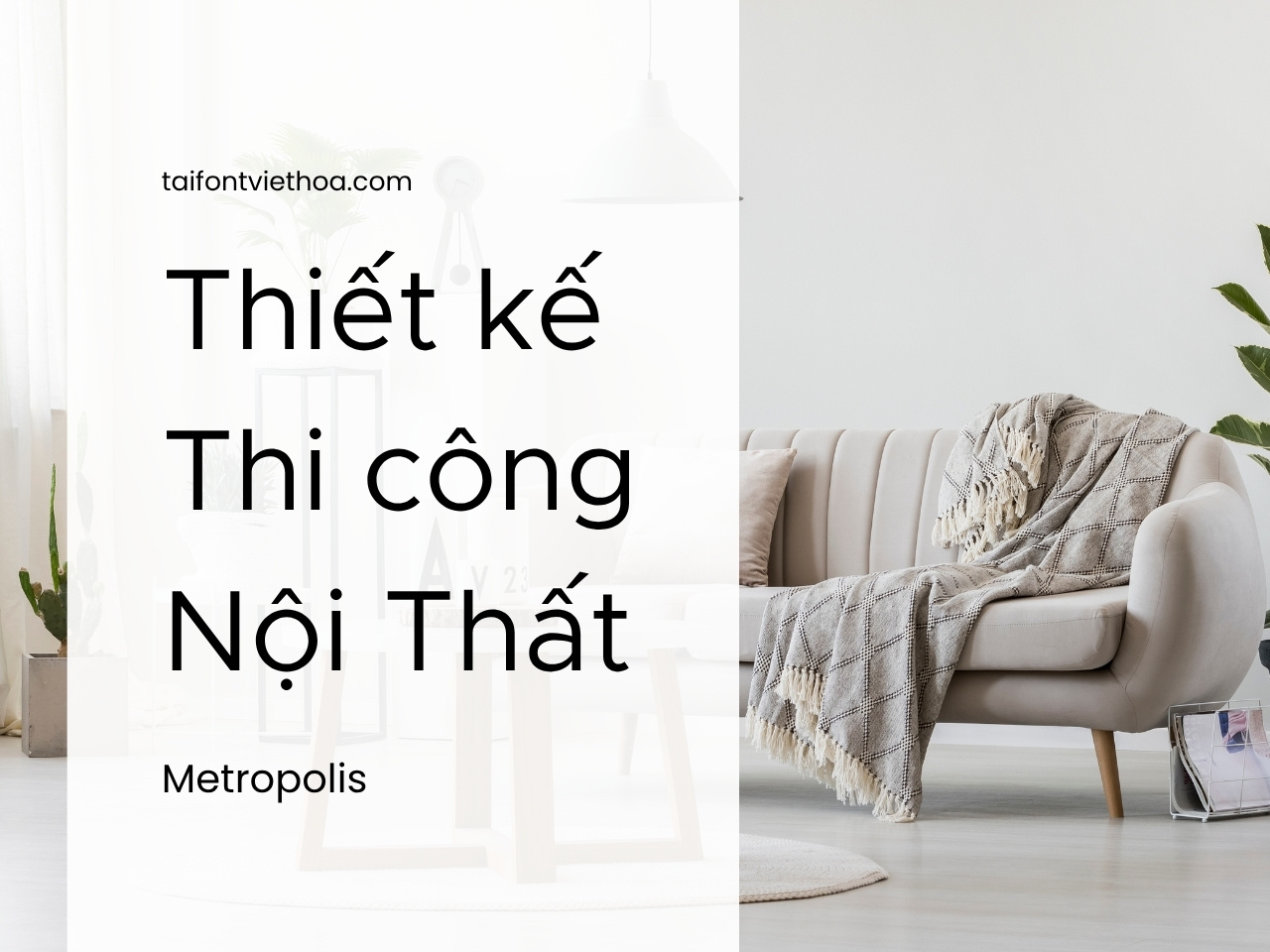
Font việt hóa Metropolis+
Tác giả Font: Chris Simpson
Giới thiệu về font Metropolis+
Metropolis là một font chữ sans-serif hiện đại theo phong cách geometric, được thiết kế bởi Chris Simpson vào năm 2020 và phát hành dưới giấy phép mã nguồn mở. Font được tạo ra như một lựa chọn thay thế cho các kiểu chữ nổi tiếng như Gotham hoặc Avenir. Phiên bản Việt hóa có tên Metropolis+ được thực hiện bởi Catterio, mang đến trải nghiệm đầy đủ cho người dùng Việt với hệ thống dấu tiếng Việt chuẩn và đẹp. Font còn hỗ trợ hơn 50 ngôn ngữ khác thông qua bảng mã Latin mở rộng, giúp nó trở thành công cụ lý tưởng cho các dự án đa ngôn ngữ. Font này được taifontviethoa.com sưu tầm, chọn lọc và thử nghiệm thực tế nhằm đáp ứng nhu cầu thiết kế đa dạng của cộng đồng sáng tạo tại Việt Nam.
Đặc điểm thiết kế và ứng dụng của Metropolis+
Metropolis+ sở hữu cấu trúc hình học rõ ràng, hiện đại, các đường nét tinh giản với độ dày đều và tương phản thấp. Font có 18 style từ Thin đến Black, bao gồm cả Italic, mang lại khả năng ứng dụng linh hoạt cho nhiều mục đích. Các ligatures và kerning được tinh chỉnh kỹ lưỡng giúp font hiển thị chuyên nghiệp cả trong nội dung văn bản và thiết kế tiêu đề.
Metropolis+ rất phù hợp với thiết kế logo, giao diện web, slide thuyết trình, bao bì sản phẩm, và các chiến dịch quảng cáo hiện đại. Đặc biệt thích hợp trong các ngành như công nghệ, bất động sản, truyền thông số, thương hiệu sáng tạo và giáo dục trực tuyến.